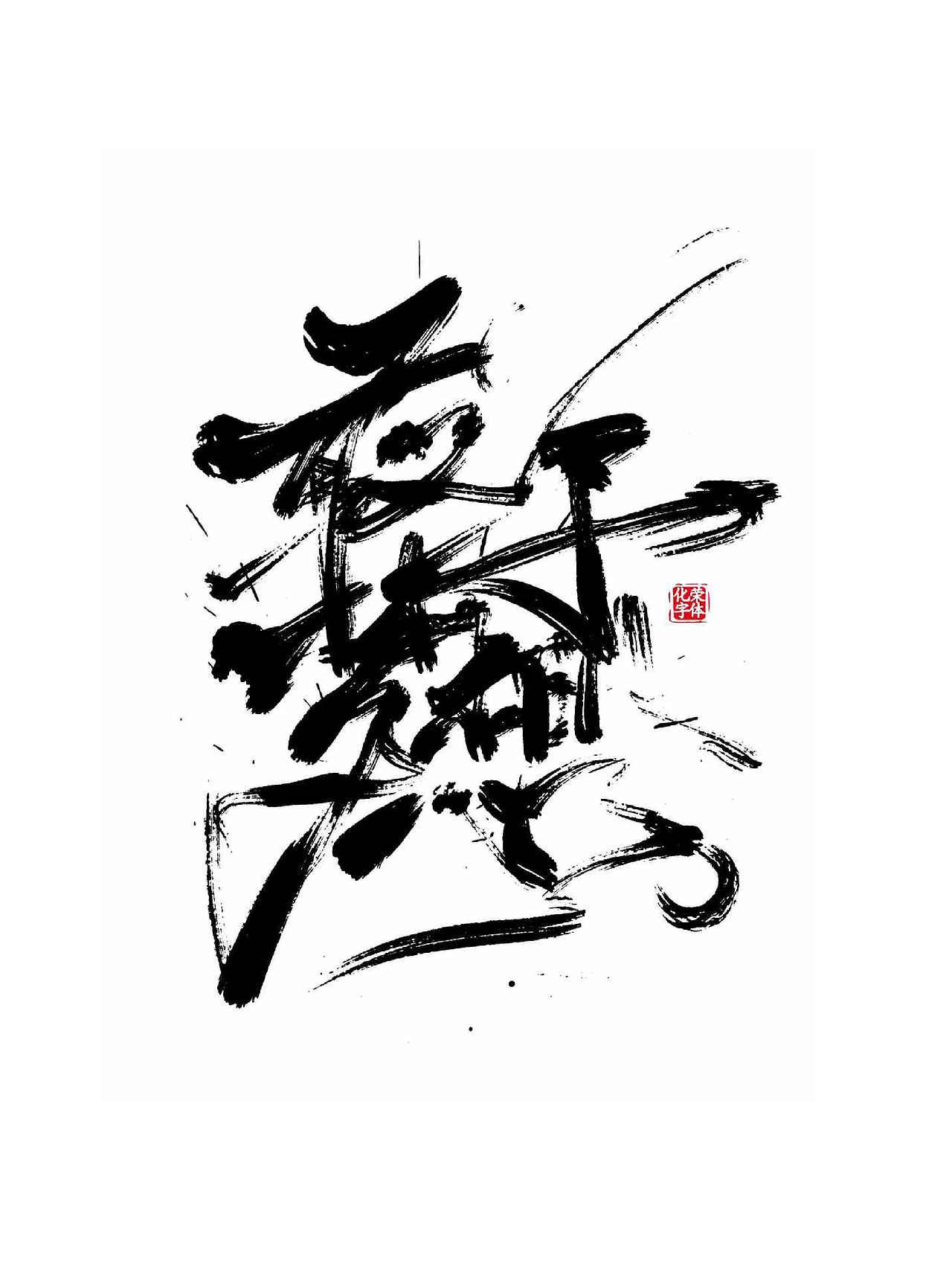
狂草字体适用于街舞嘻哈涂鸦个性潮流HIPHOP 服装字体
狂草字体适用于街舞嘻哈涂鸦个性潮流HIPHOP 服装字体(图ZMzg3OTg2NjQ0) - 字体/字形 - 站酷设计师涂鸦字体设计化荣原创素材 - 站酷ZCOOL
狂草字体适用于街舞嘻哈涂鸦个性潮流HIPHOP 服装字体(图ZMzg3OTg2NjQ4) - 字体/字形 - 站酷设计师涂鸦字体设计化荣原创素材 - 站酷ZCOOL
狂草字体适用于街舞嘻哈涂鸦个性潮流HIPHOP 服装字体(图ZMzg3OTg2NjUy) - 字体/字形 - 站酷设计师涂鸦字体设计化荣原创素材 - 站酷ZCOOL